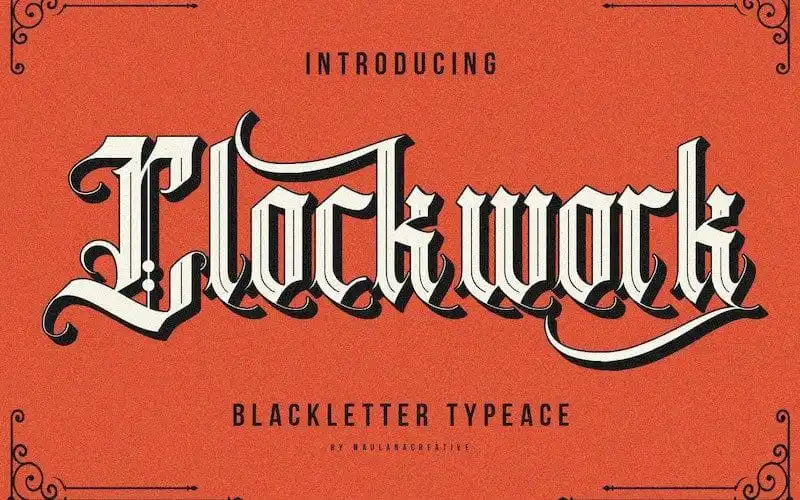
Olá! Estou aqui a Clockwork Font, uma família de tipografia Blackletter Condensada inspirada na cultura antiga dos games primitivos e no antagonismo. Esta fonte moderna tem um toque vintage que remete à década de 1800, mesclando o melhor do clássico com os elementos modernos. A Clockwork Blackletter Vintage é uma mistura cuidadosamente feita de letras manuscritas Victorianas e tipografia clássica. Ela inclui alternativas que adicionam um toque de adrenalina ao seu uso, lembrando-nos da nossa inspiração nos games primitivos dos anos 1970 e 80. A Hamilton é o designer por trás desta fonte única e poderosa, que transmite tanto a força quanto a simplicidade. Seja para rotular seus designs gráficos ou criar uma identidade visual memorável para sua marca, Clockwork Font não deixará ninguém indiferente.